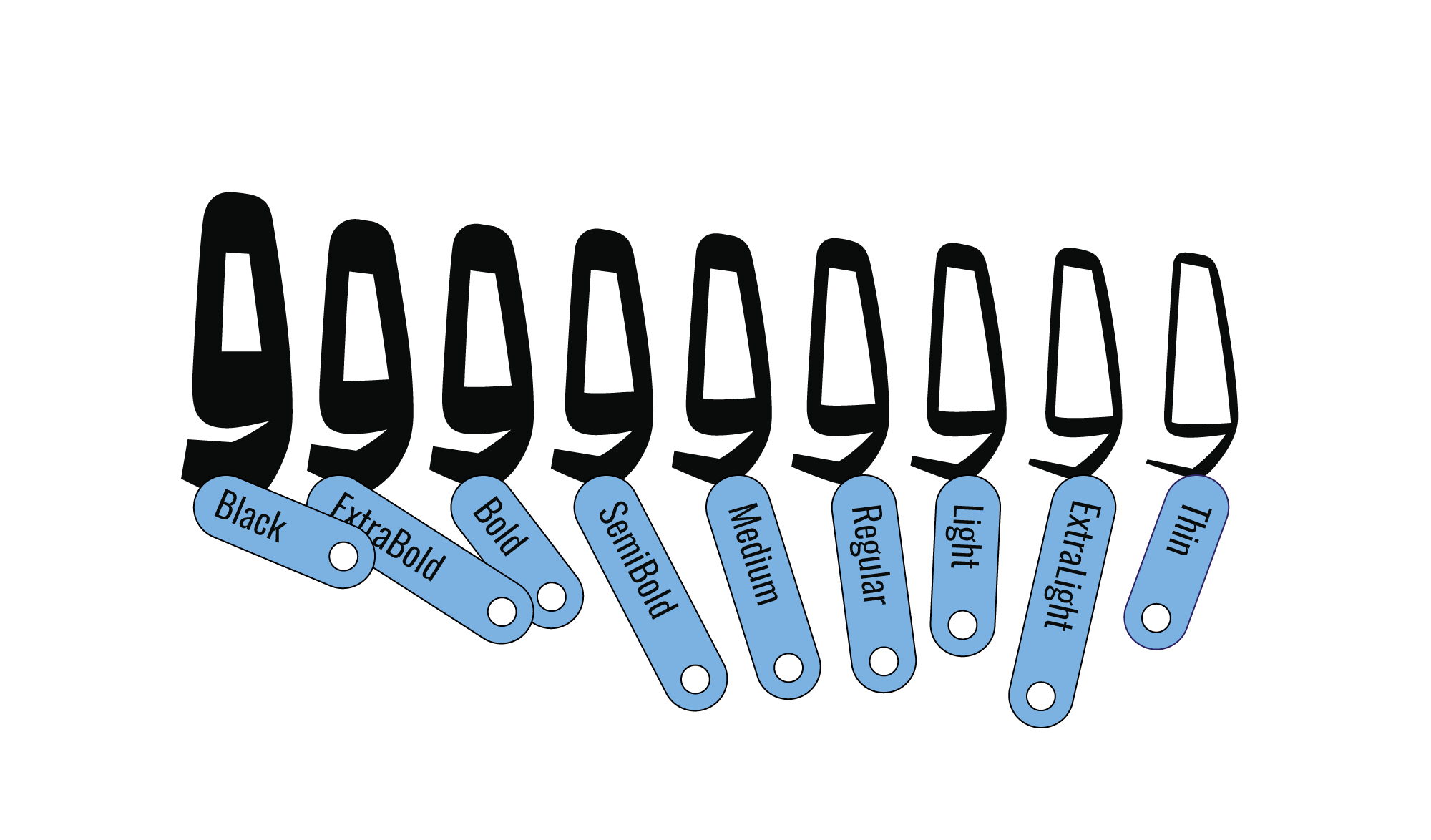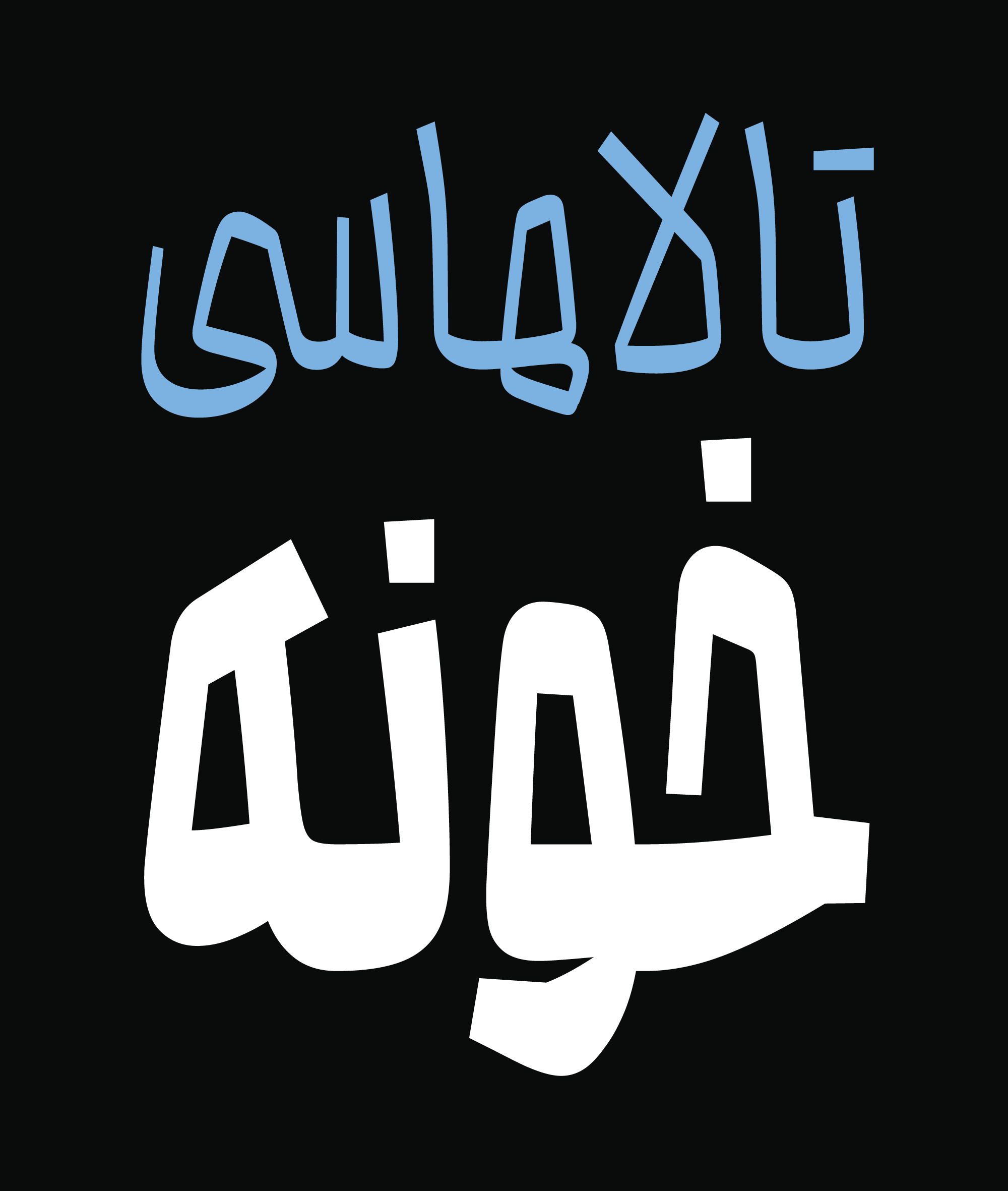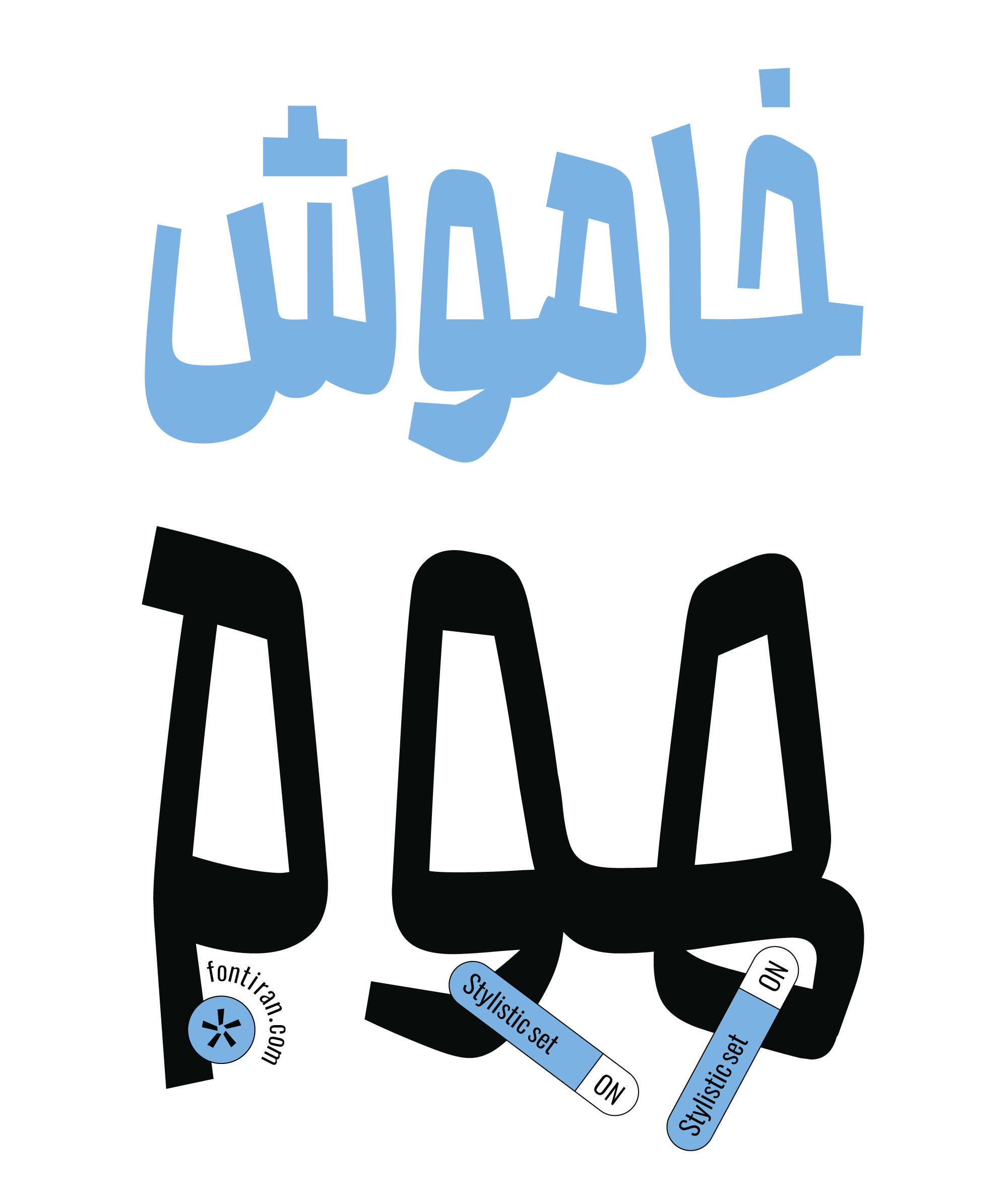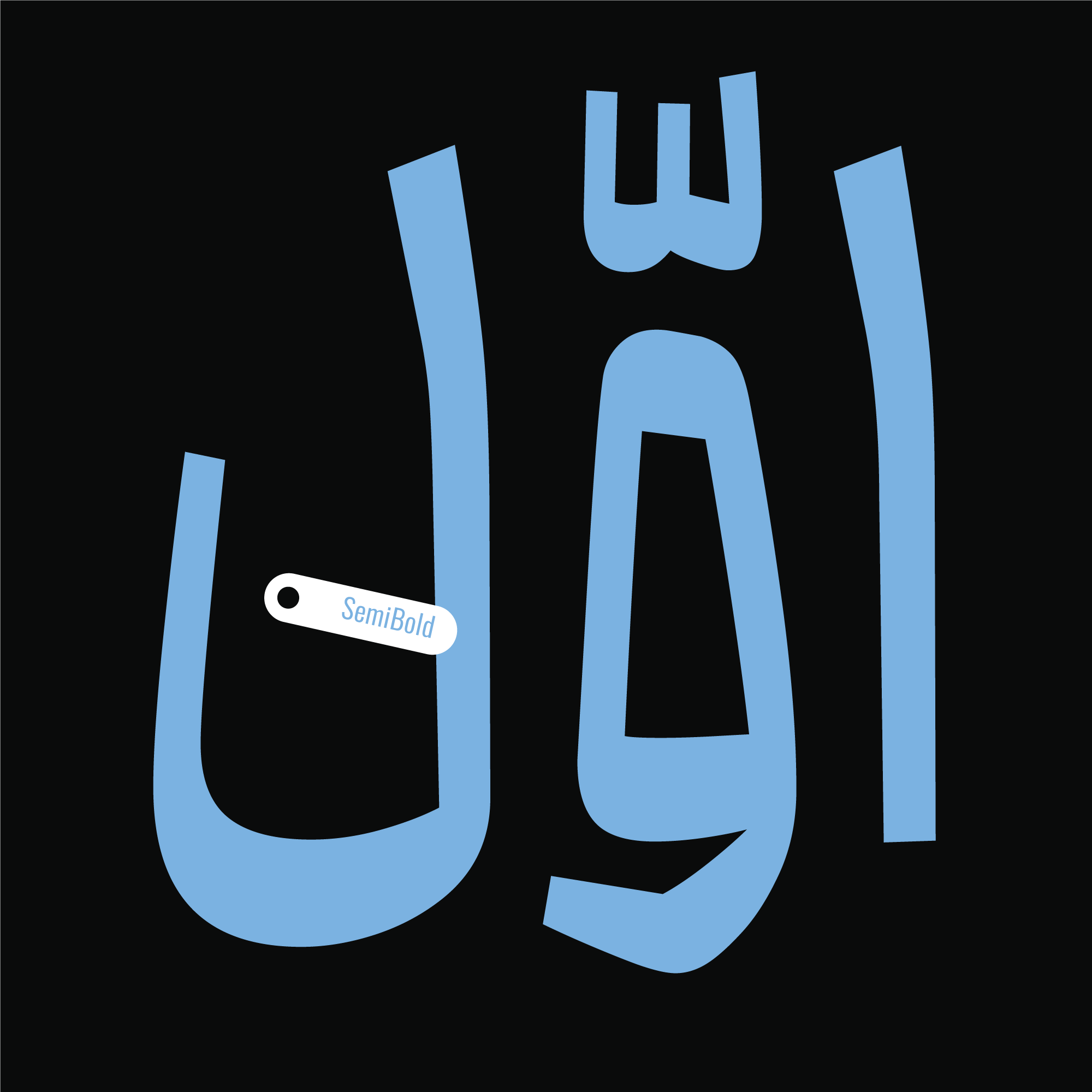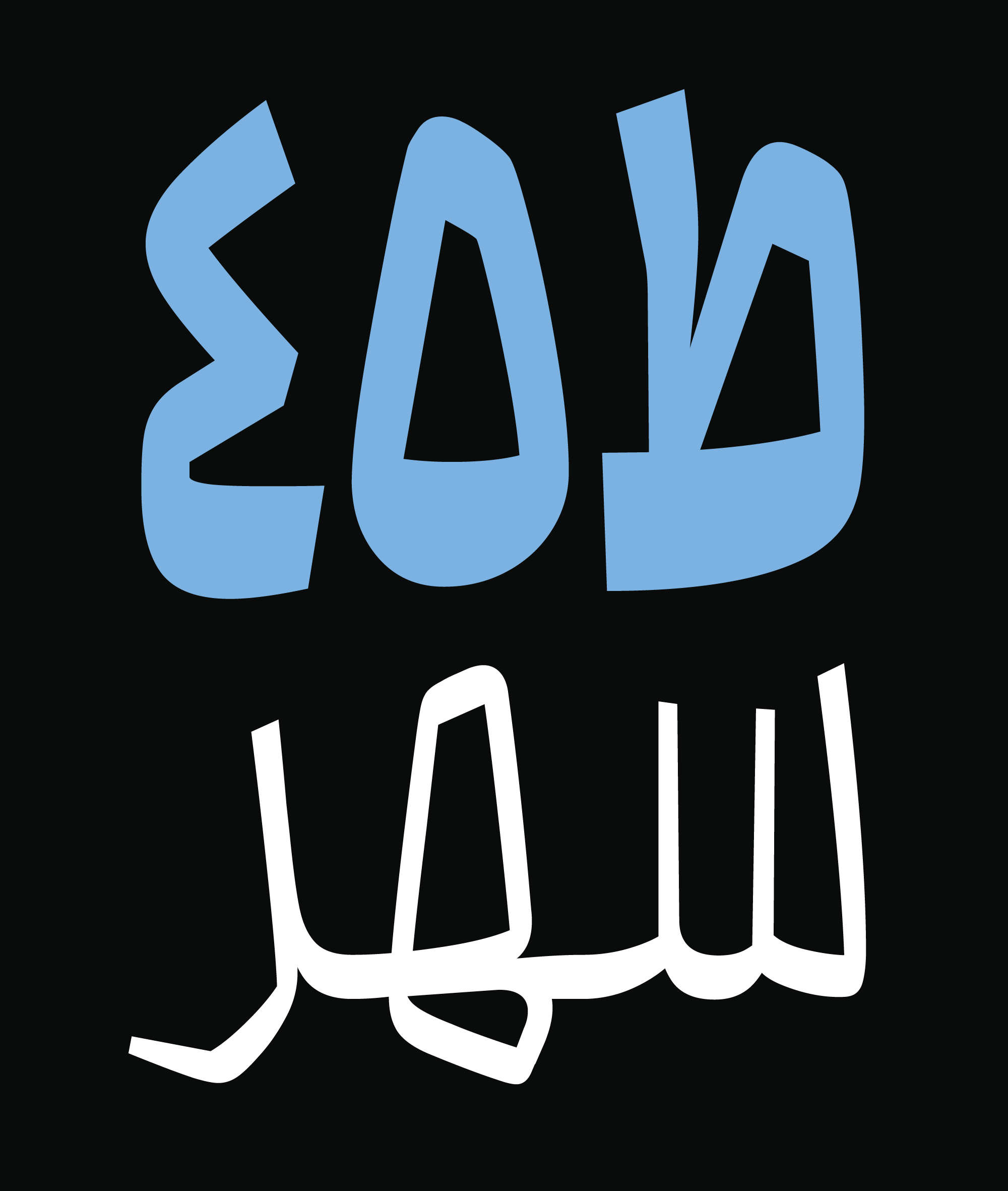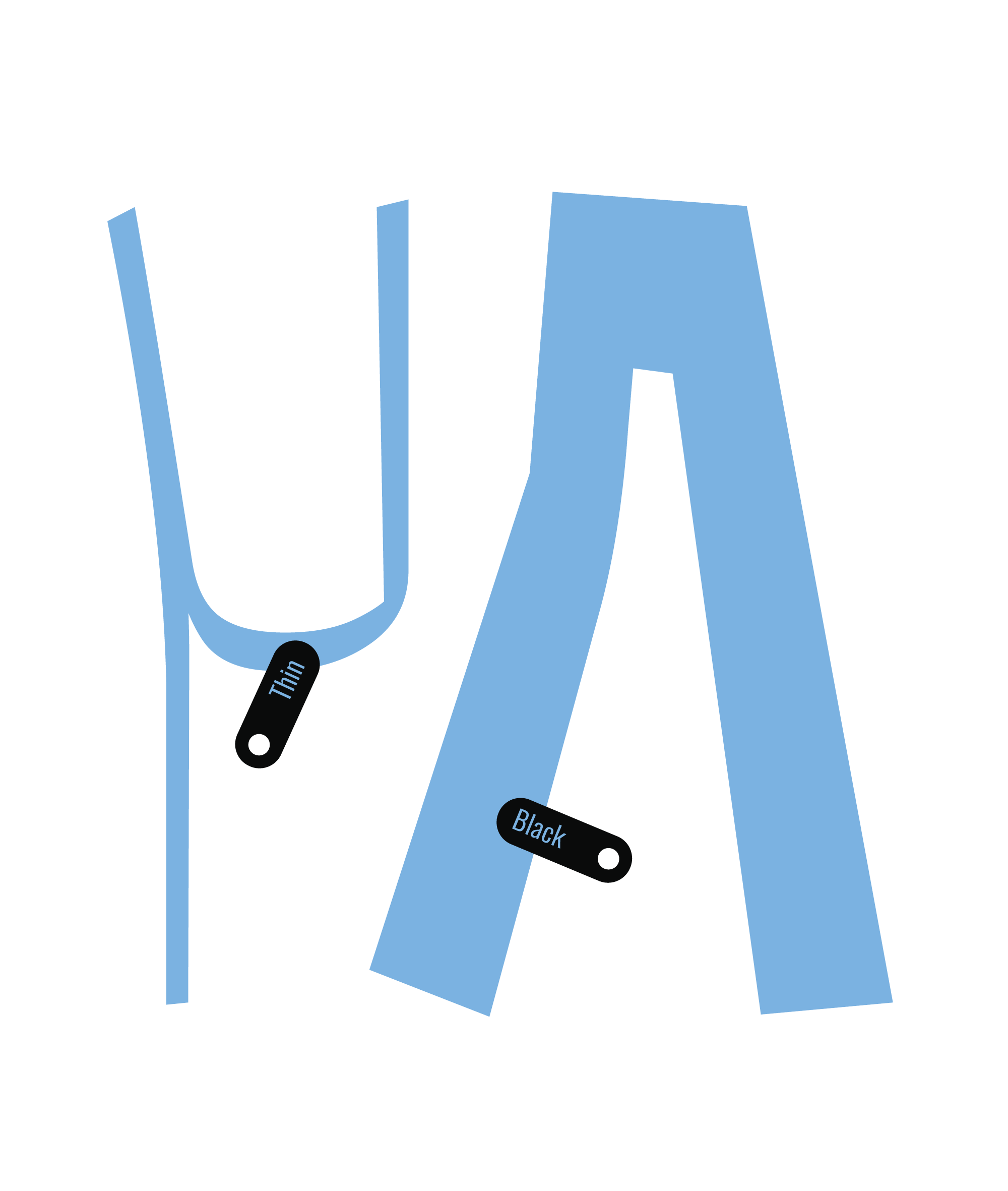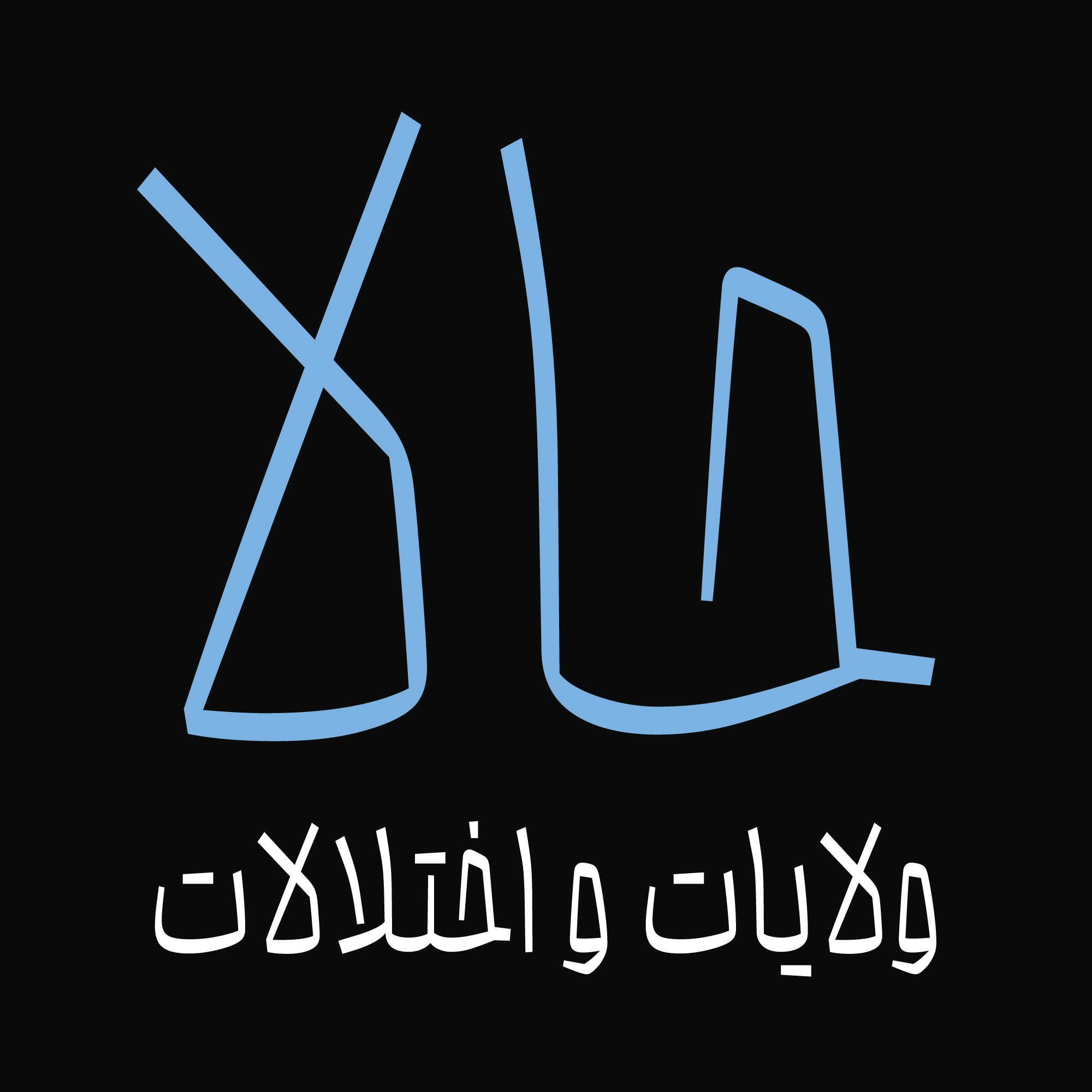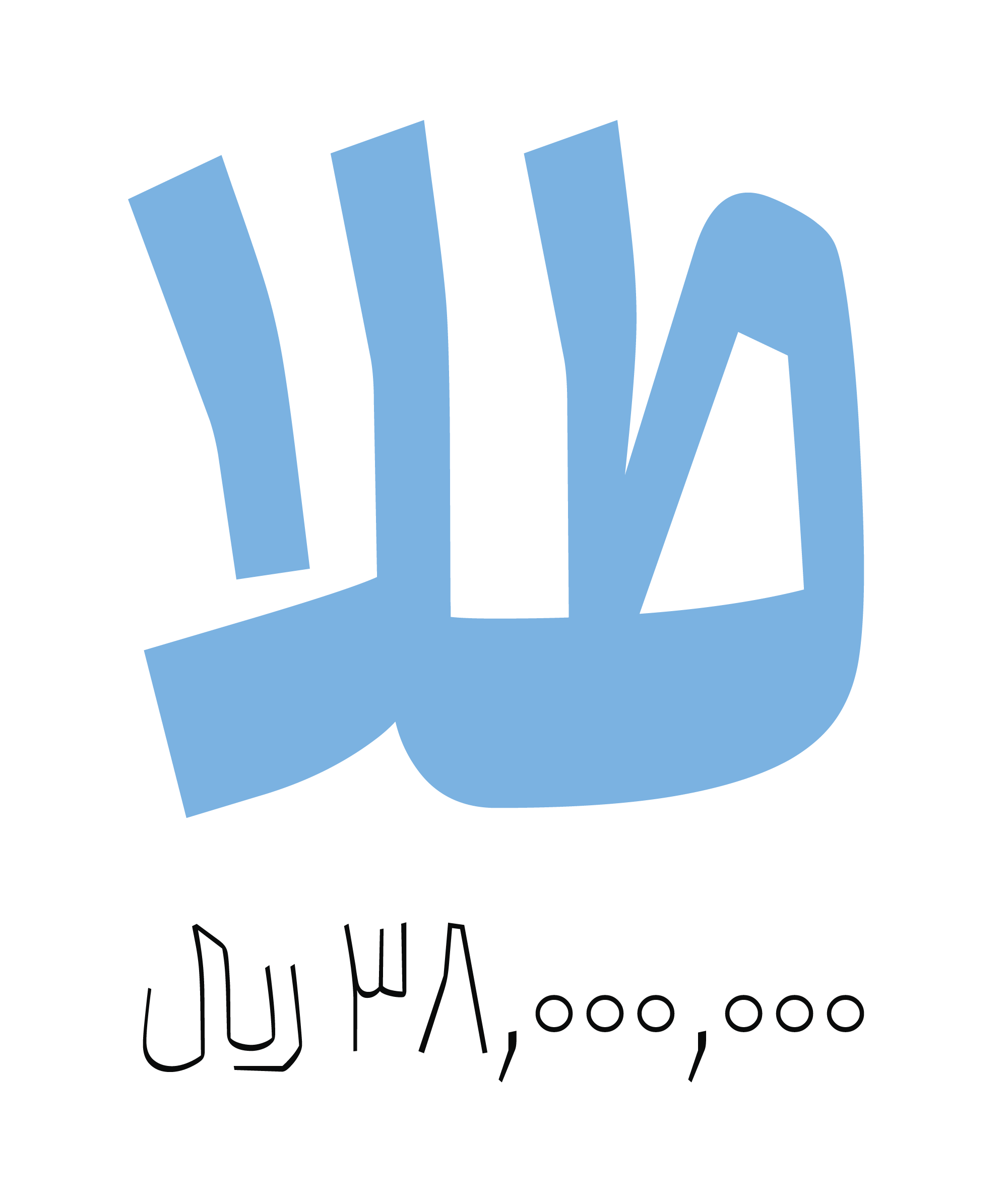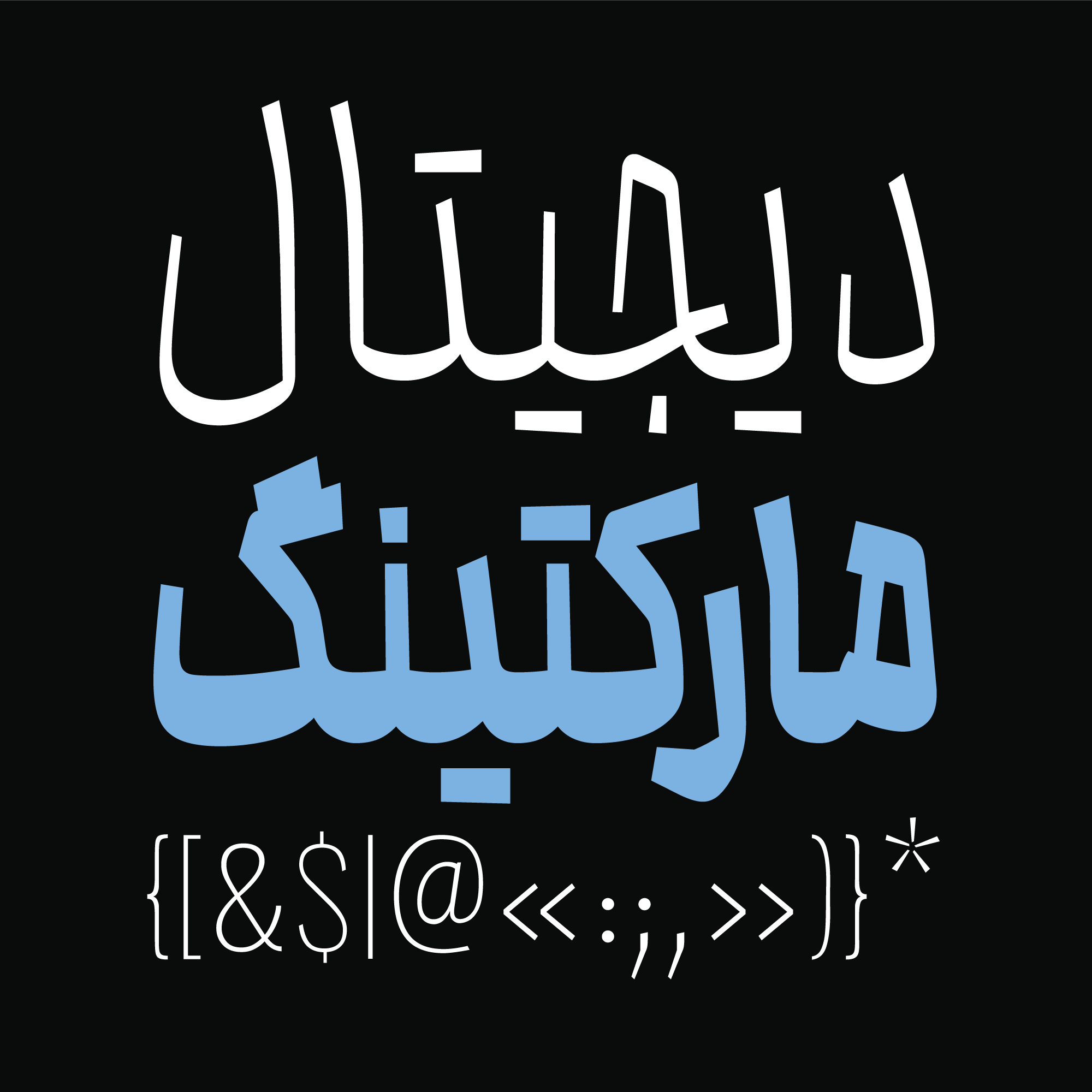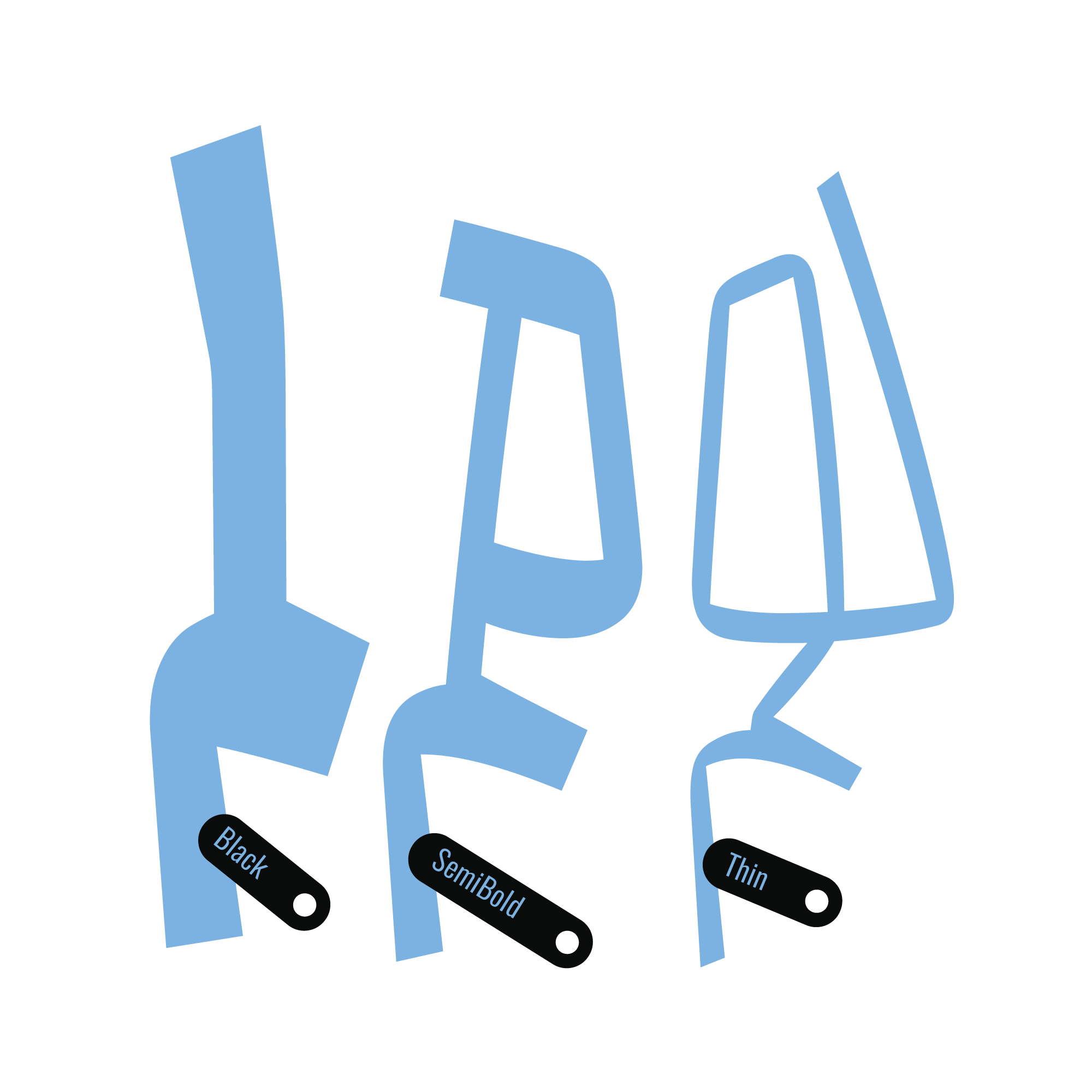
اولین اتودهای فونت «محال» در سال ۱۴۰۱ شکل گرفت. در اولین روزها رسیدن به نقطهی امروزینِ این تایپفیس برایم بسیار صعب و پیچیده بهنظر میرسید، امّا «محال» قدم به قدم راه خودش را پیدا کرد تا یکی از اولین تایپفیسهایی باشد که با حفظ روحیات رسمالخط فارسی، در راستای محور عمودی ارتفاع گرفته باشد.
در طراحی تایپفیس «محال» ویژگیِ عمودی بودنِ فرم حروف، همزمان با توجه به ویژگیهای رسمالخط و خوانایی، چالشهایی را به همراه داشت که از مهمترین آنها کنترل فضای بین حروف و استقلالِ حلقههای باز و بسته، کنترل ریتم خطوط عمودی، توجه به ارتفاع حروف و دندانهها و میزان وابستگی به بیسلاین (خط کرسی) بود. اکنون «محال» -هرچند ادعایی در بسیار خوانا بودن ندارد امّا- تلاش کرده است که قدمی هر چند کوچک امّا رو به جلو در اعتلای خط زیبای فارسی باشد.
محال روحیهای معترض دارد و حرفی که با آن بنویسید را فریاد میزند! هرچند در عین پر انرژی بودن، گاهی ساکت و درونگراست.
این فونت دارای حس و حالِ نمایشی است و جزییات و بازیگوشیِ فرمِ حروف باعث میشود که این فونت برای تیتر و متنهای کوتاه مناسب باشد.
ادمین شبکههای اجتماعی، بلاگرها، استارتاپها، طراحان بازی، وب و اپلیکیشن میتوانند مهمترین کاربران فونت «محال» باشند.
تنوع وزنها در فونت «محال»
محال خانوادهی فونتی در ۹ وزن است که از وزن بسیار نازک تا بسیار تیره را شامل میشود. در سبکترین (نازکترین) وزن، کنتراست ضخامتِ حروف کم است تا حدی که شبیه به حروفِ فونتهای مونولاین رفتار میکنند. هرچه که وزنِ فونت تیرهتر میشود برای کنترل فضای فرمِ حروف، کنتراست ضخامت بیشتر میشود.
حروف و ترکیبهای جایگزین
برای «محال» تعدادی حرف و جفتحرفِ جایگزین طراحی شده است. حروف جایگزین در دسته Stylistic Alternates قرار دارند که به صورت Stylistic Set نیز در دسترس هستند. ترکیبهای جایگزینی که با حرف «ی»، «ر» و «ن» ختم میشوند بهصورت لیگیچرهای Standard Ligatures در دسترس هستند. ترکیبهای جایگزینی که به حروف دیگر مانند «م» ختم میشوند بهصورت لیگیچرهای Discretionary Ligatures در دسترس هستند.
حروف و ترکیبهای فونت «محال» برای انتشار پُست و استوری در شبکههای اجتماعی قدرتمند هستند و کلماتی که با این فونت نوشته میشوند چشمگیر خواهند بود!
پشتیبانی از زبان عربی و انگلیسی، اردو و کردی
فونت «محال» برای زبان فارسی و عربی طراحی شده است و زبانهای اردو، کردی و انگلیسی را نیز پشتیبانی میکند.